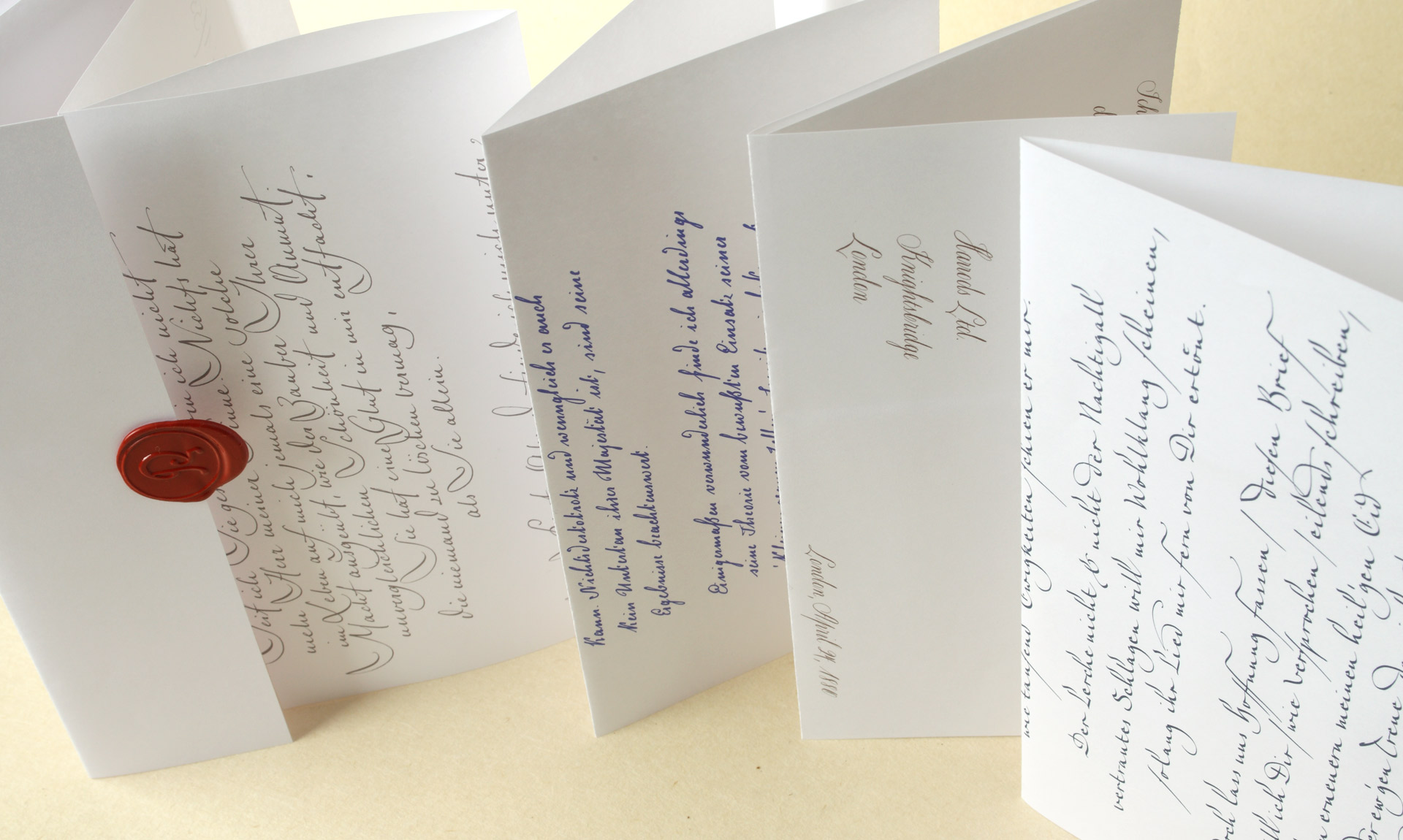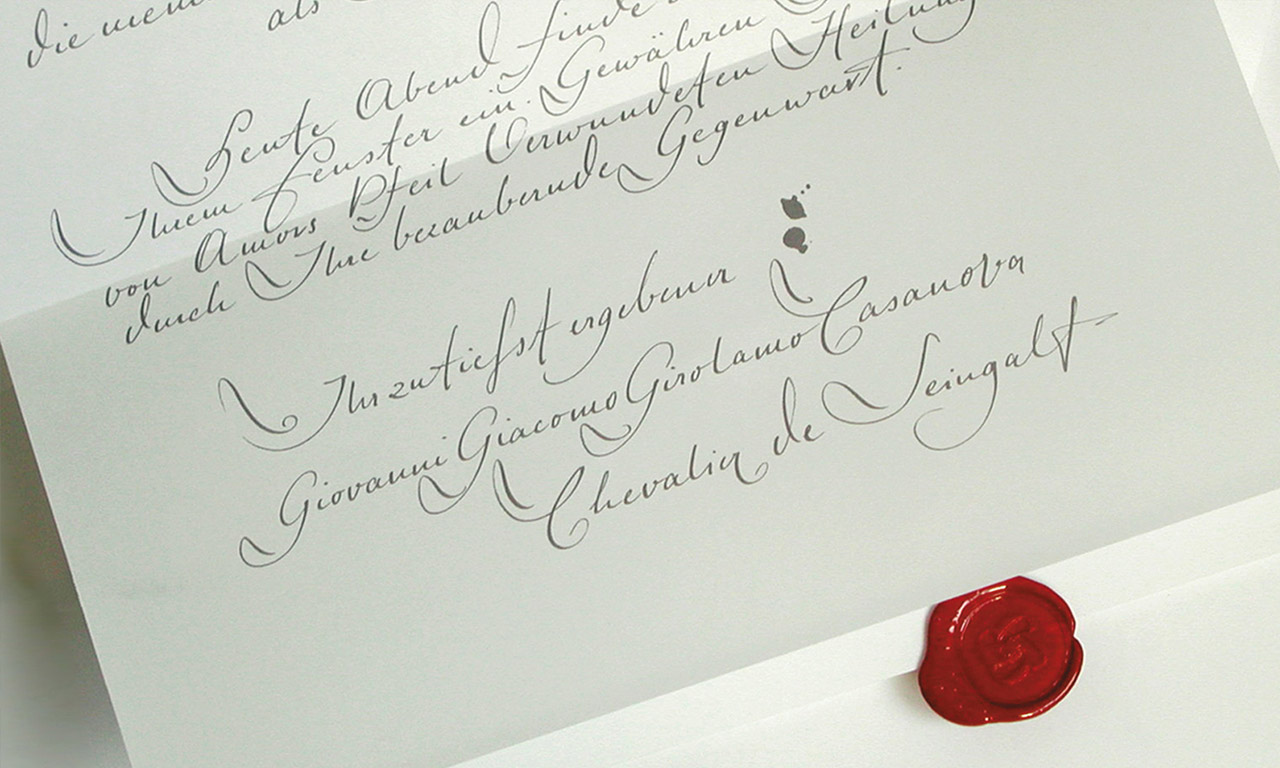
DEUTSCHEpapier / Mythos Musterbuch
Recherche, Handschrift im Duktus verschiedener Jahrhunderte, Lieferung der Feindaten für den Druck.
Jeder Papiersorte des Musterbuchs wurde ein Brief/eine Handschrift von »Persönlichkeiten« aus verschiedenen Jahrhunderten zugeordnet. Nach Recherchearbeiten (größtenteils an Originalen) habe ich die Schriften der damaligen Zeit mit ihren typischen Merkmalen unter Berücksichtigung heutiger Lesbarkeitskriterien in unsere Zeit transferiert.
Abbildung oben:
Handschrift-Interpretation Casanova, 18. Jahrhundert
Abbildung unten:
Weitere Handschrift-Interpretationen aus dem Mythos Musterbuch:
Casanova, 18. Jahrhundert / Miss Marple, 20. Jahrhundert / Abraham van Helsing, 19. Jahrhundert / Romeo, 16. Jahrhunder (v.l.)